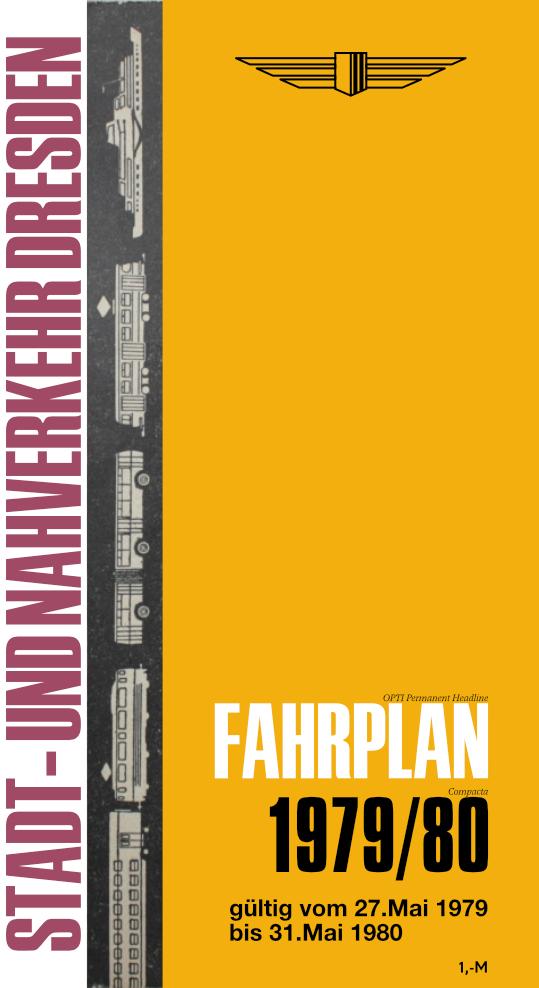
Suche Schriftart von Fahrplanheft Dresden
An den Symbolen wird noch gearbeitet. Als Programm habe ich Affinity Designer gewählt.
Mich verwundert auch etwas das rundgelutschte der Buchstaben und das N sowie K wirkt sehr klobig.
Seit wann gibt es dieses Design, den ältesten den ich gefunden habe ist von 1976.
Ich dachte erst an die Permanent aber die hat andere Zahlen, S und R kommen aber hin.
Die Permanent scheint es zu sein. Für die Zahlen wurde dann mit ziemlicher Sicherheit die Compacta verwendet. Vielen Dank für den Tipp.